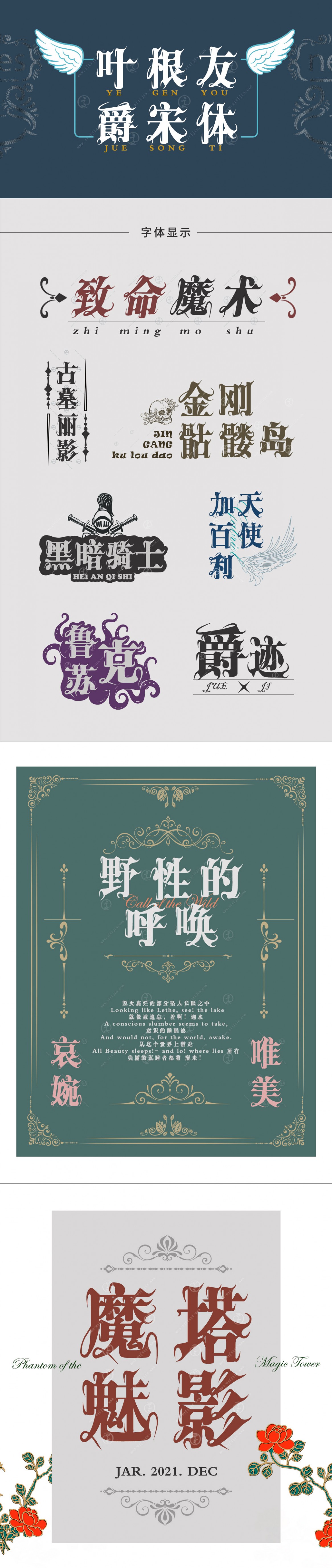
葉根友爵宋
字體作者:葉根友
創(chuàng)作年代:2012年
字體字?jǐn)?shù):6763個中文漢字以及其他英文字母和阿拉伯?dāng)?shù)字
字體介紹
一款創(chuàng)意來自于撲克人物紅桃K的造型,將書法藝術(shù)與撲克人物相結(jié)合的創(chuàng)意,對于字體設(shè)計來說是一種跨界思維的體現(xiàn)。